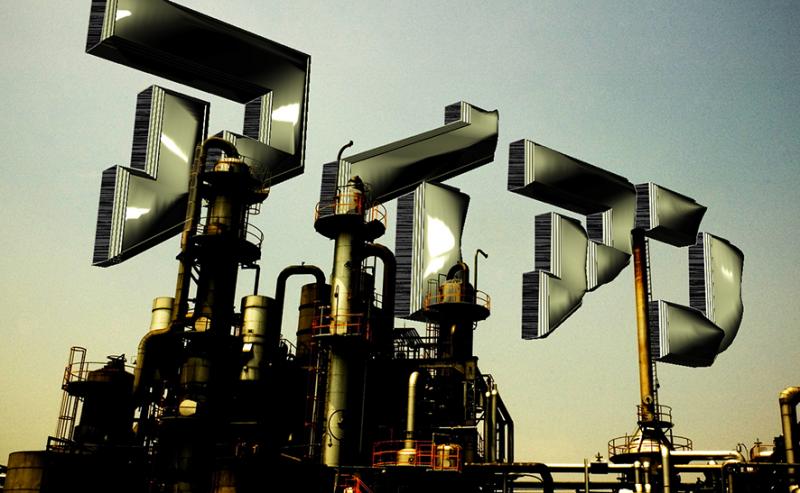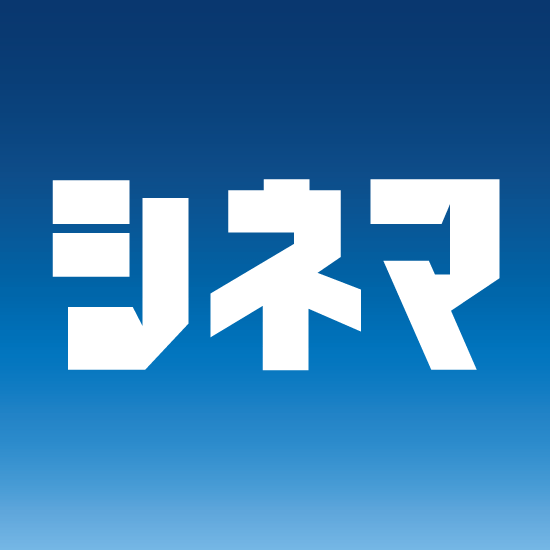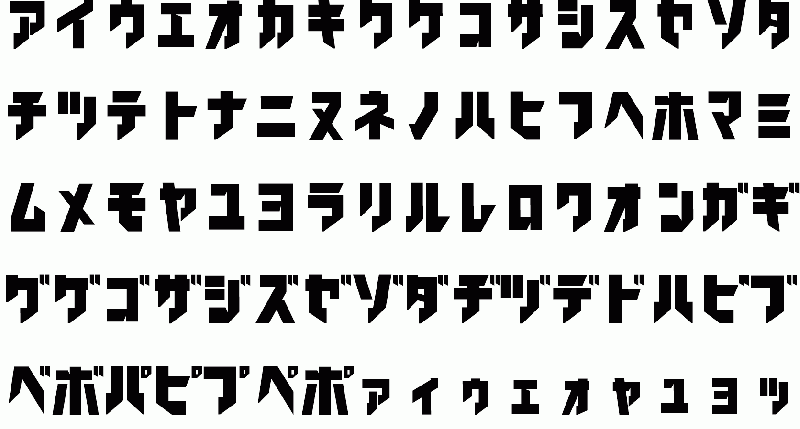
アイアン・フォント|Chiba Design|和文・欧文・デザイン書体のダウンロード販売|フォントファクトリー
商用利用可能なオリジナルフォントです。Open Type・ 2バイト・カタカナのみ。アウトライン化可能。直線が力強い無骨なイメージのフォントです。ロゴの作成などにお使いください。
アイアン・フォント